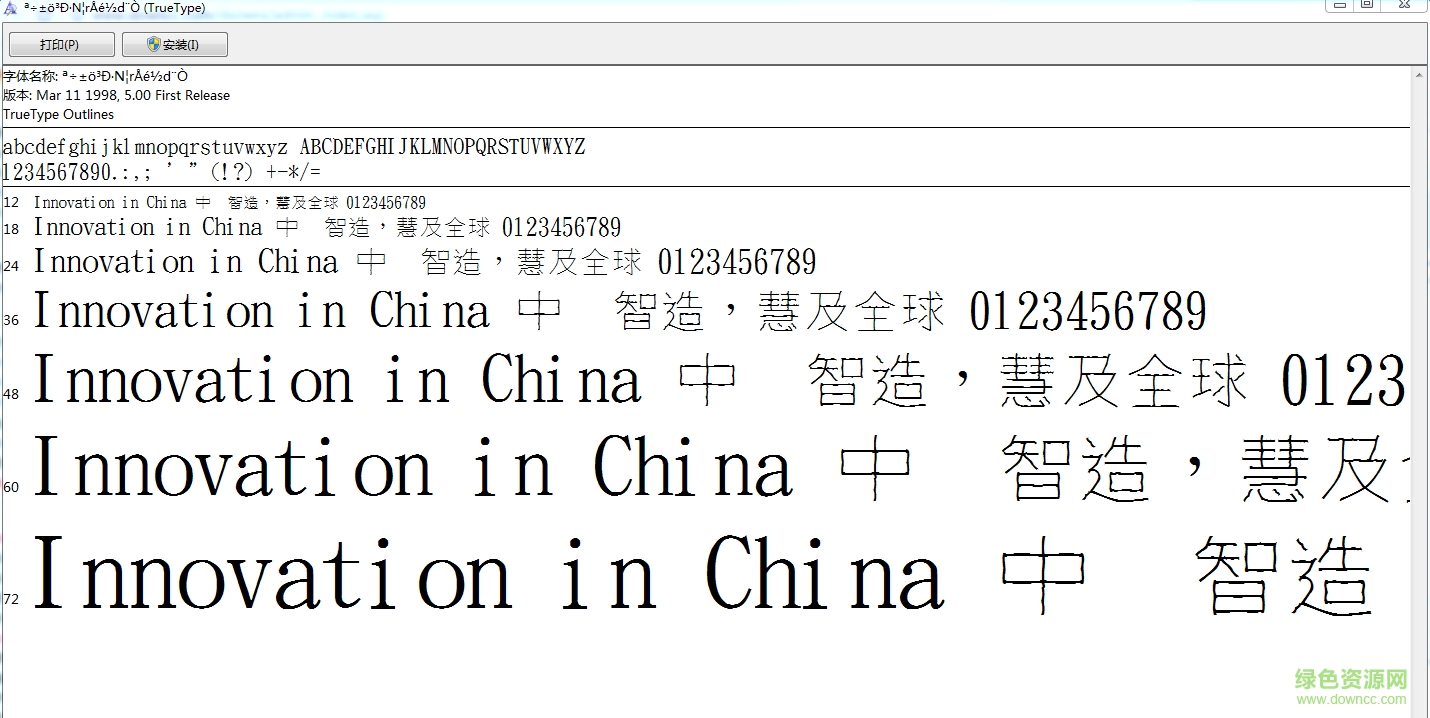
金梅創(chuàng)意字體范例字體是一款金梅類非常具有創(chuàng)意的范例字體軟件,作為范例字體給人非常正式正規(guī)的感覺,適合比較正規(guī)的場合,也深得廣大書法家喜歡,還有更多好看字體盡情期待,歡迎到綠色資源網(wǎng)下載體驗(yàn)!
金梅創(chuàng)意字體范例是一款金梅類創(chuàng)意十足的正規(guī)字體,字體效果比較整齊,非常正式,喜歡范例字體的朋友可以下載使用看看效果如何。